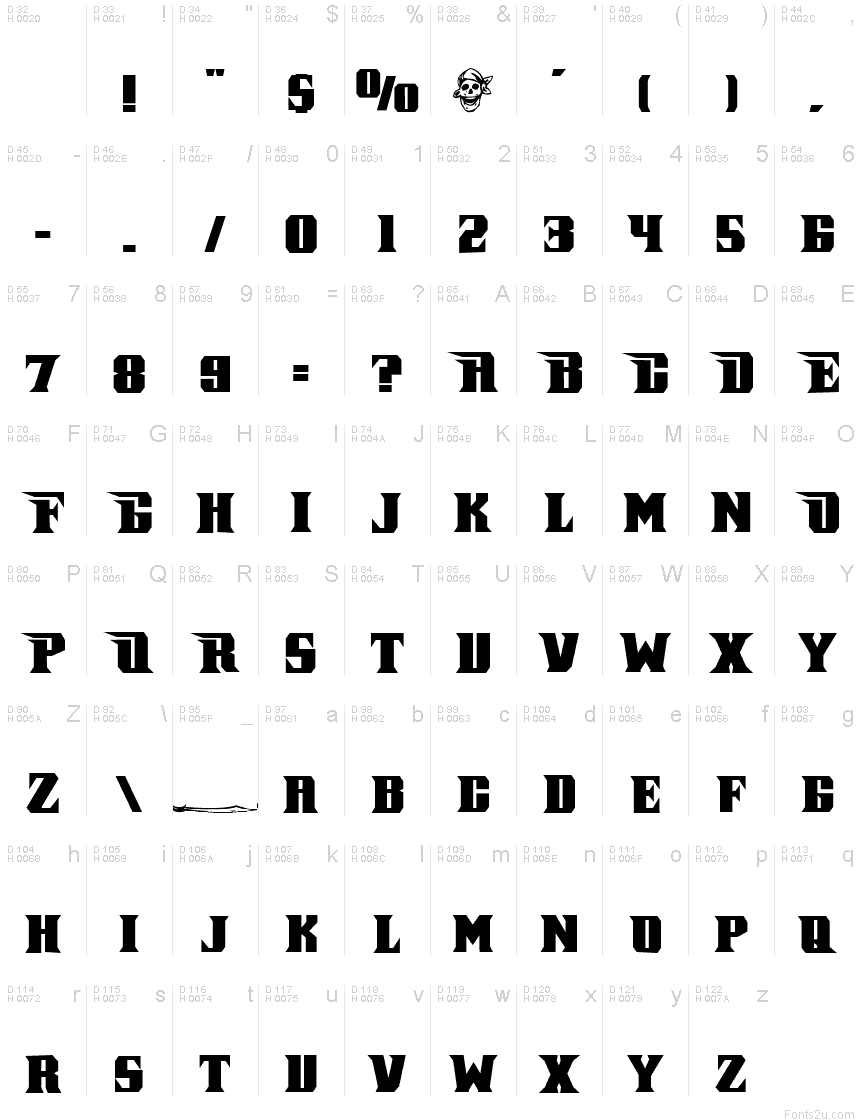
Pirate Keg od Sharkshock Productions to darmowy, piracki krój typu display, który oddaje surowy klimat starego szyldu tawerny. Litery są duże, ciemne i solidne jak beczka, z przyciętymi rogami, klinowymi cięciami i kwadratowym rytmem, co nadaje alfabetowi charakter „roboczy”, przypominający pieczątkę, zamiast wygładzonego, współczesnego wykończenia.
Świetnie sprawdza się w nagłówkach plakatów, na etykietach, w tytułach gier, brandingu barów i grafikach eventowych, gdzie potrzebujesz wyrazistego, teatralnego efektu bez zbędnej przesady. Jako darmowy font, sprawdzi się również w krótkich tekstach na okładki, monogramach i szkicach logo, ponieważ te masywne wielkie litery zachowują swój charakter nawet przy krótkich słowach.
Pirate Keg